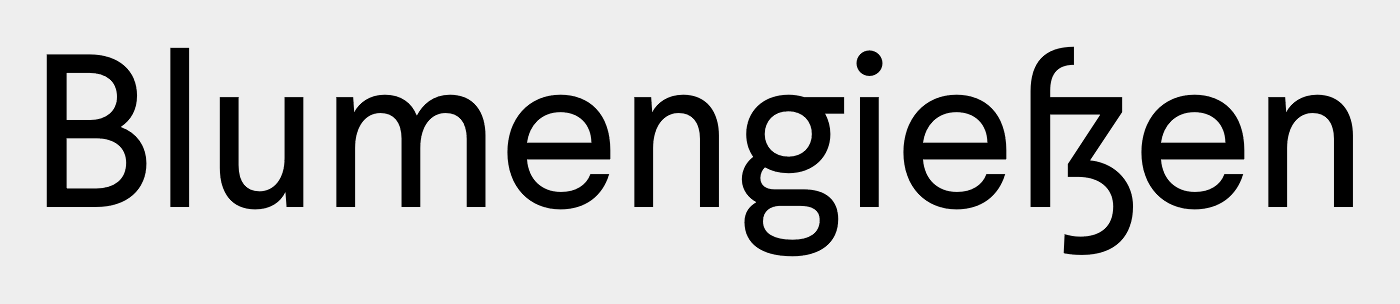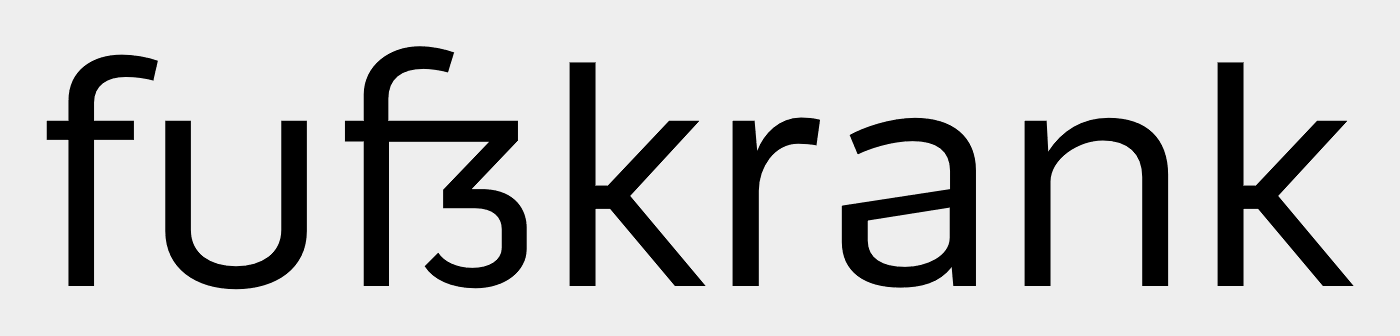
typen mit sz-ligatur
Trotz der vielen Liebhaber dieser Form hier: Ich halte eigentlich nicht soviel davon, dass das ſz (oder auch ſs) in "modernen" Schriften anstelle des regulären ß verwendet wird. Es gibt einfach dem Schriftbild (finde ich) eine historische Note oder Retrophilie, die ich in den wenigsten Fällen gebrauchen kann. Diese "altbackene" Form lässt sich auch nicht gerade einfach Kunden vermitteln. Ich hatte das Problem schonmal in der Vergangenheit mit der Pill Gothic, die ich an dieser Stelle diesem Thread beisteuern möchte:
Ich hatte sie für den Produktkatalog einer amerikanischen Firma verwendet und als es im Anschluss um die deutsche Fassung ging, waren wir über diese Form des Eszetts doch etwas erstaunt. Dabei hat die Schrift ja sogar zwei Alternativ-ß – nur leider nicht über OpenType ersetzbar. Man hätte den Buchstaben manuell bzw. über "Finden–Ersetzen" austauschen müssen. Ich hätte mir diese Arbeit vielleicht noch gemacht, aber der Agentur, die den deutschen Katalog gesetzt hat, wollte ich damit nicht auf die Nerven gehen.
ſz oder ſs – Gerne als OT-Alternative (es wäre doch prima geeignet für die Historical Forms), aber bitte, bitte nicht als reguläres ß. Die Arquitecta hätte ich gerne gekauft. In Ermangelung eines gebräuchlichen Eszetts werde ich das aber wohl lassen.
Und bei aller Vergangenheitsliebe: Das Lang-ſ braucht – abgesehen vom Setzen in historischem Kontext – auch kein Mensch mehr. Danke, Ralf, für deinen treffenden Artikel diesbezüglich: http://www.typografie.info/3/page/artikel.htm/_/wissen/wach-stube-wachs-tube.
Bzgl. Larsseit:
Die zugehörige Foundry Type Dynamic ist mir ja aufgrund der signifikanten Sonderangebote und nicht auffindbaren Webpräsentation etwas »unheimlich«.  :-?
Als großer Freund dieser Bauform muß ich sagen, daß dieses Teil in der Pill wirklich abscheulich ist. Mit viel gutem Willen kann man das höchstens noch als fȝ-Ligatur durchgehen lassen, aber selbst dazu fehlt es dem ȝ an der Unterlänge, was ja dann auch prompt zu dieser absurden Breite führt. Viel schlechter kann man das nicht machen.
Mit viel gutem Willen kann man das höchstens noch als fȝ-Ligatur durchgehen lassen,
Eher ſʒ (ezh) als ſȝ (yogh), mit ezh mit seiner Herkunft als z mit Unterschlinge wäre es ja korrekt, insbes. mit Heyse als ß-Herleitung. *)
Im Vergleich ezh/yogh sieht ja die Sulzbacher Form ja eher nach "falschem" yogh-Abklatsch aus ...
aber selbst dazu fehlt es dem ȝ an der Unterlänge,
Beim ß als vollwertigem Buchstaben statt Ligatur wäre es ja gerechtfertigt, das ezh hochrutschen zu lassen, also ohne Unterlänge.
was ja dann auch prompt zu dieser absurden Breite führt. Viel schlechter kann man das nicht machen.
Wenn hochgestubst ohne Unterlänge müsste man aber auch drauf verzichten, den oberen (e)z(h)-Querstrich separat ins ſ einmünden zu lassen, und es mit dem oberen Bogen des ſ zusammenlegen ...
*) Richtiger sähe es dann aber aus, wenn auch das normale z als ʒ gestaltet ist, wobei sich dann die Frage stellt, wie man das "echte" ezh gestalterisch vom z unterscheiden will ...
Ich halte eigentlich nicht soviel davon, dass das ſz (oder auch ſs) in "modernen" Schriften anstelle des regulären ß verwendet wird. Es gibt einfach dem Schriftbild (finde ich) eine historische Note oder Retrophilie, die ich in den wenigsten Fällen gebrauchen kann.
Passen muss es schon zum Font ...
Warum sollte man sich bei der Formensuche in modernen Fonts nicht auch mal an alten Formen anlehnen ...
Aber wie gesagt gehört dann eigentlich auch ein ʒ als z in den Font, wenn man das ß als ſʒ gestalten will ...
ſs ist eigentlich nach aktuell an Heyse angelehnter Rechtschreibung die falsche Herleitung ... Sieht aber dem Sulzbacher ß noch halbwegs ähnlich, deswegen wohl so beliebt und m.E. auch meist unauffällig.
Und bei aller Vergangenheitsliebe: Das Lang-ſ braucht – abgesehen vom Setzen in historischem Kontext – auch kein Mensch mehr.
Mich täte es reizen, es wieder häufiger zu nutzen. Aber da wäre in Font sinnvoll, bei dem sich das ſ besser vom f unterscheidet, also bspw. ſ ohne Serife links oben, dafür Unterlänge, die das f nicht bekommt.
In so einem Kontext bräuchte man aber neben einem Sulzbacher ß auch noch eine Ligatur ſs für div. "ehemaligen ß" nach Adelung und ſʒ für wenige Fälle, wo das nötig wäre, mir ist gerade das Bsp. dafür entfallen, wurde hier vor einer Weile verwendet das Wort ... wie in Nachtszene, weiter oben im Faden hatte ich es ja *alzheimertatter* ;-)
Eher ſʒ (ezh) als ſȝ (yogh), mit ezh …
Danke für die Richtigstellung in Bezug auf ʒ und ȝ, ich habe hier ein Problem mit meinem PopChar, das ʒ zu lokalisieren. Ich meinte aber keine ſʒ-Ligatur, sondern ein fʒ-Ligatur (die natürlich niemand braucht).
Warum sollte man sich bei der Formensuche in modernen Fonts nicht auch mal an alten Formen anlehnen ...
Weil man damit sehr viele Leser irritiert?! Aus diesem Grund lehne ich prinzipiell extravagante Formen in Mengensatzschriften ab. Diese einzelnen Buchstaben schreien dann einfach aus dem Satzbild heraus "Schaut her, ich bin was ganz besonderes!". Ich denke, dass Schriftgestalter, die solche Formen als Standard einsetzen und nicht als OpenType-Alternativen (wie gesagt: Gerne!), die Einsatzmöglichkeiten ihrer Schriftschöpfung ziemlich stark limitieren. Natürlich sollen auch extravagante Schriftgestaltungen ihren Platz haben. Aber es stört mich schon, wenn in bestimmten Mengensatzschriften, die eigentlich einen neutralen, zeitlosen, aber dennoch subtil-eigentständigen Charakter haben, dann plötzlich doch ein Buchstabe auffällig aus der Reihe tanzt.
Mir fällt dazu das fürchterliche ſs in der alten Version der Freight Sans ein, eine sonst ganz wunderbare Schrift, die aber mit diesem "Makel" (für mich) völlig unbrauchbar war. Mittlerweile wurde das ja glücklicherweise korrigiert.
ich verstehe was du meinst, man sollte aber schon einen unterschied zwischen extravaganterform und historischer form machen. trotzdem wäre es natürlich angebracht zumindest eine alternative form zu hinterlegen.